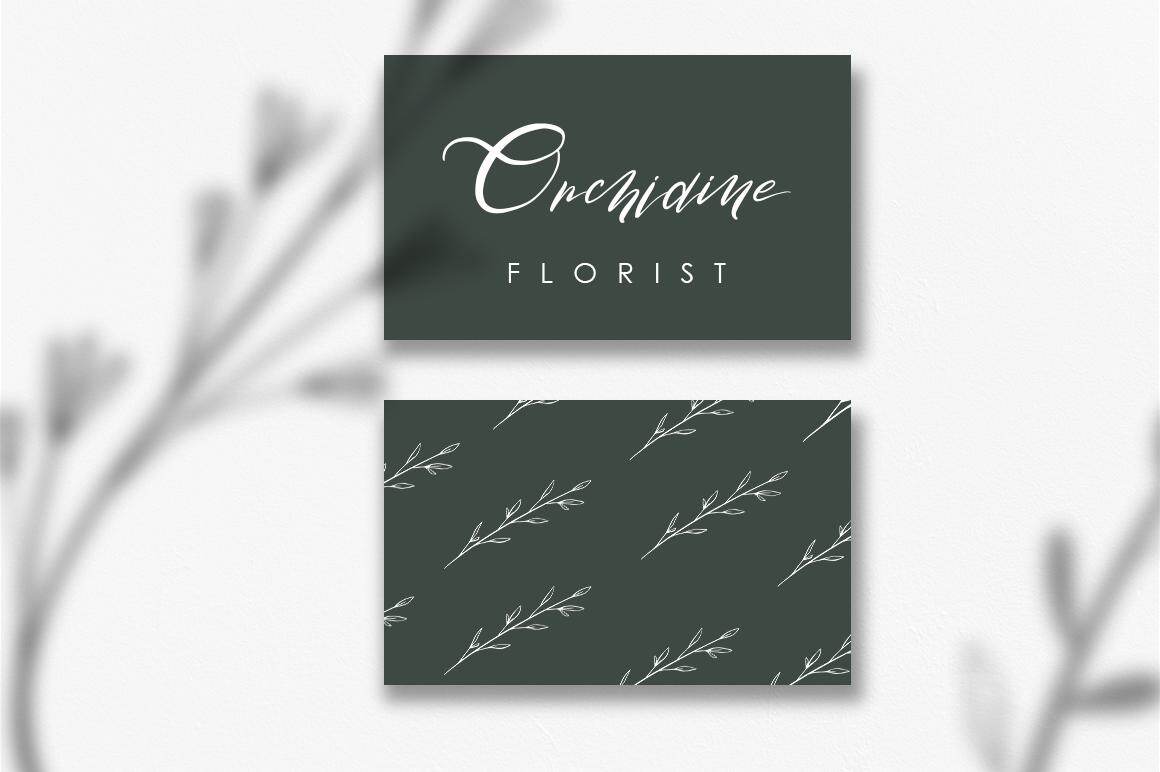
Rosemallow是Lovely字体,此字体适用于品牌、徽标、邀请函、文具、婚礼设计、社交媒体、手写报价、产品包装、商品、博客设计、书籍/封面等。Rosemallow是Lovely字体,此字体适用于品牌、徽标、邀请函、文具、婚礼设计、社交媒体、手写报价、产品包装、商品、,blogdesign、Book/Covertitle和更多。